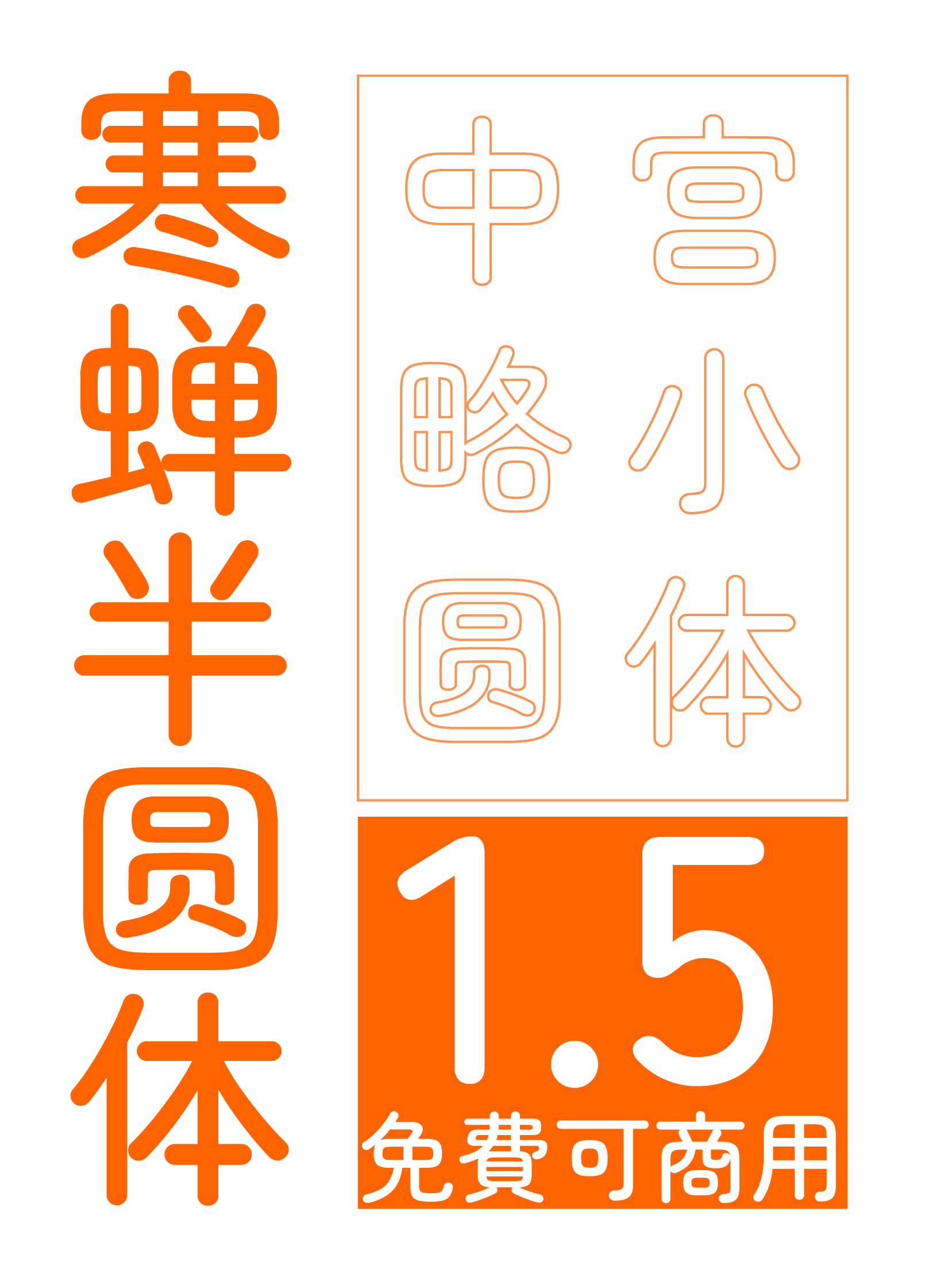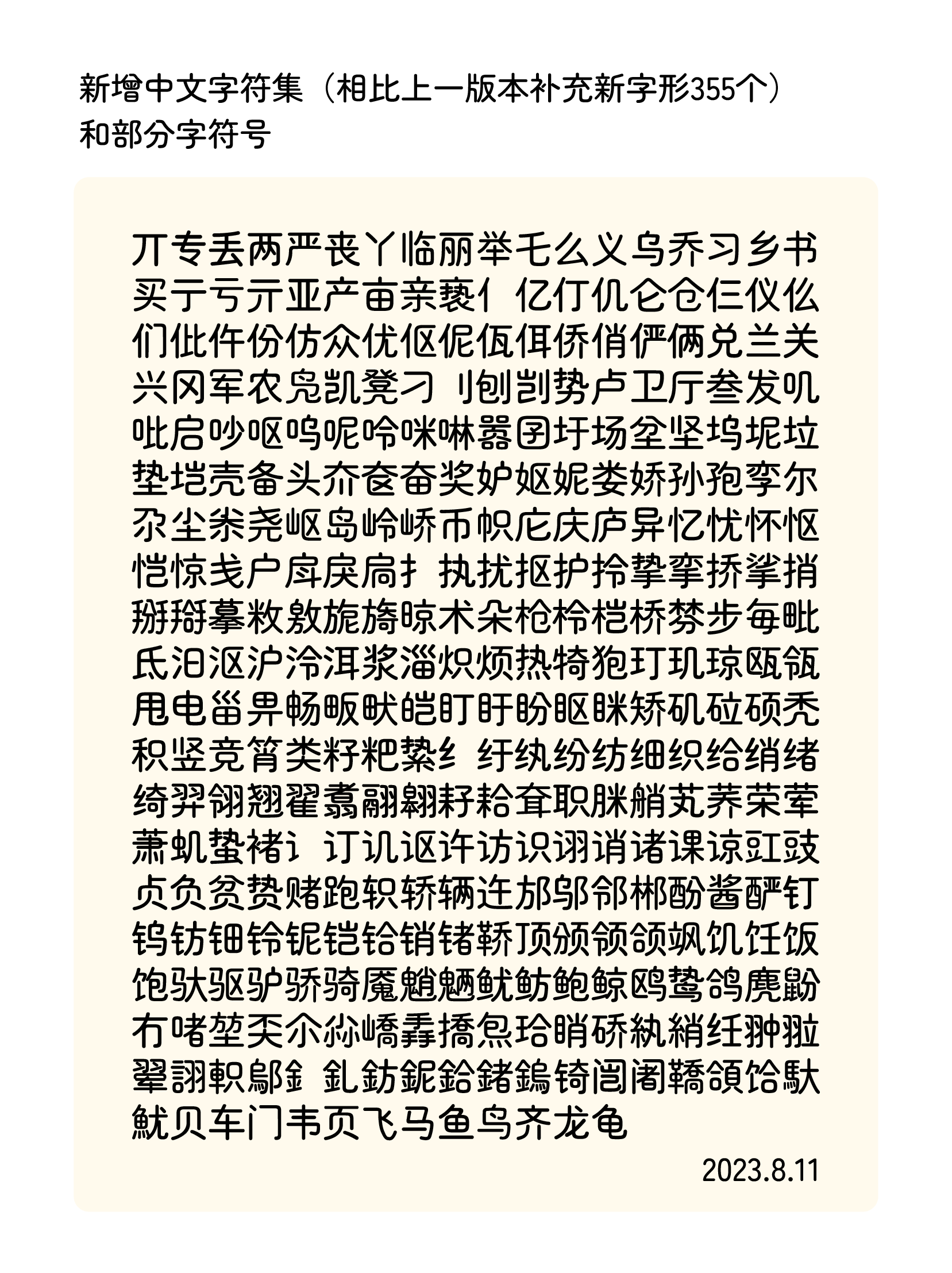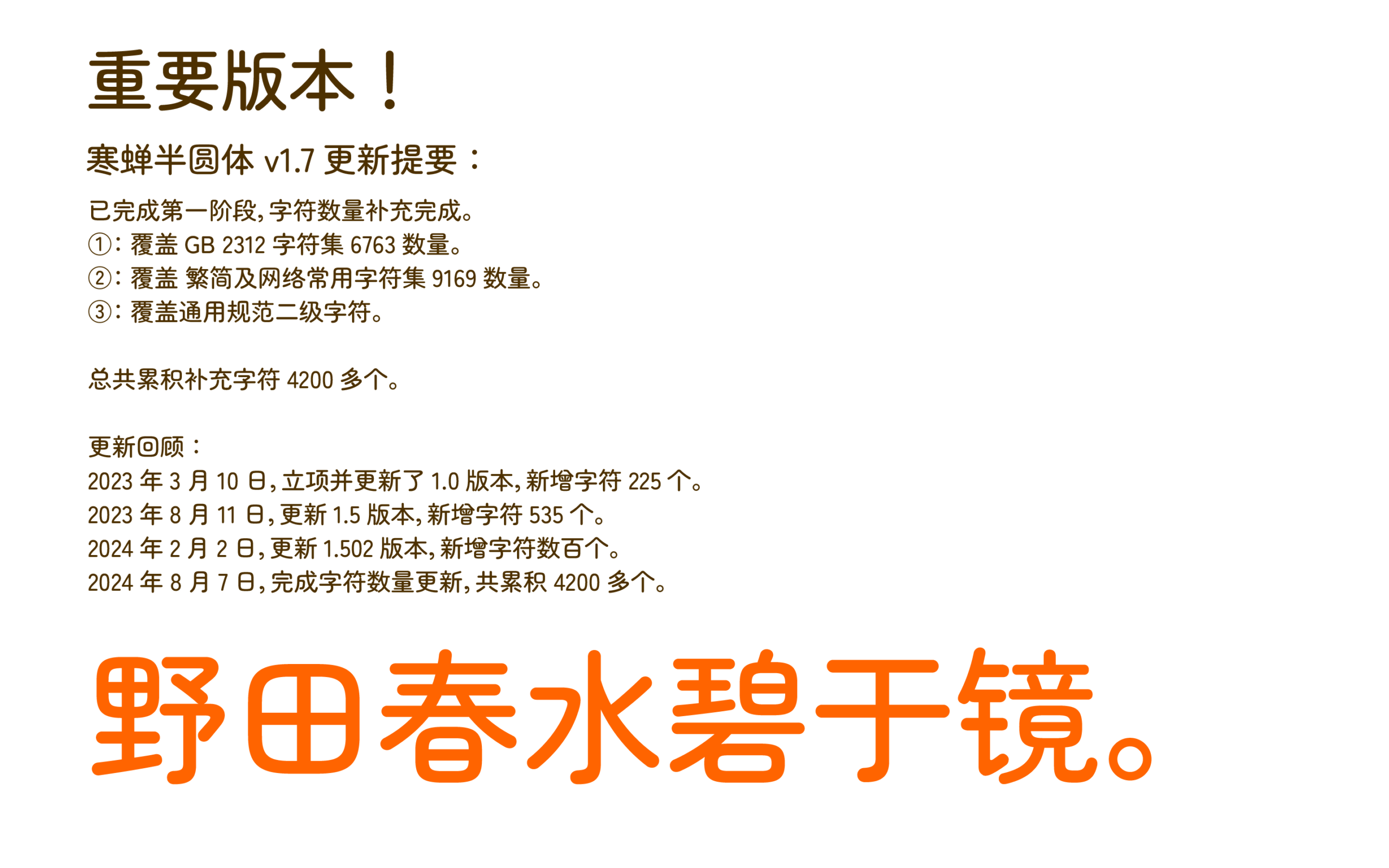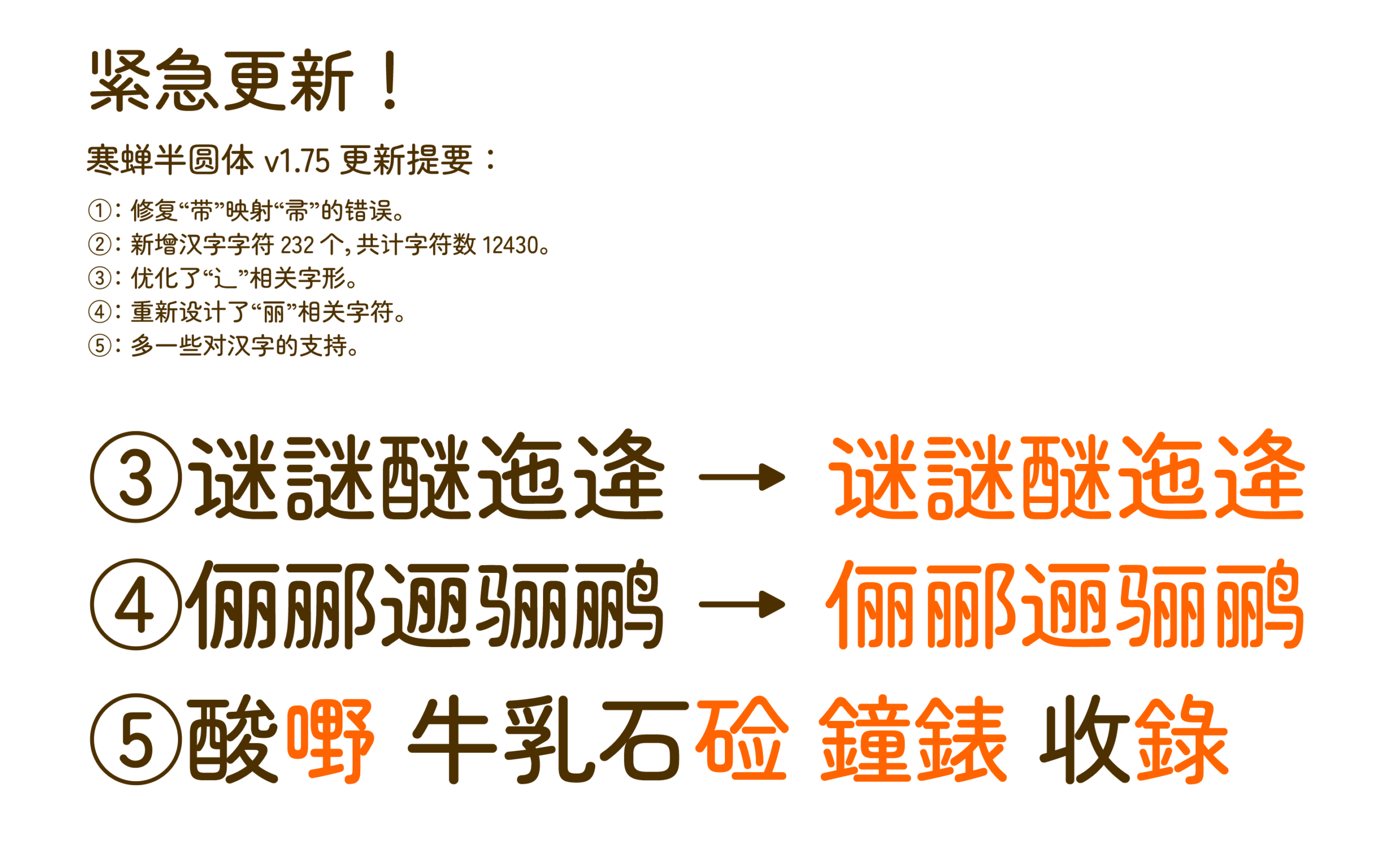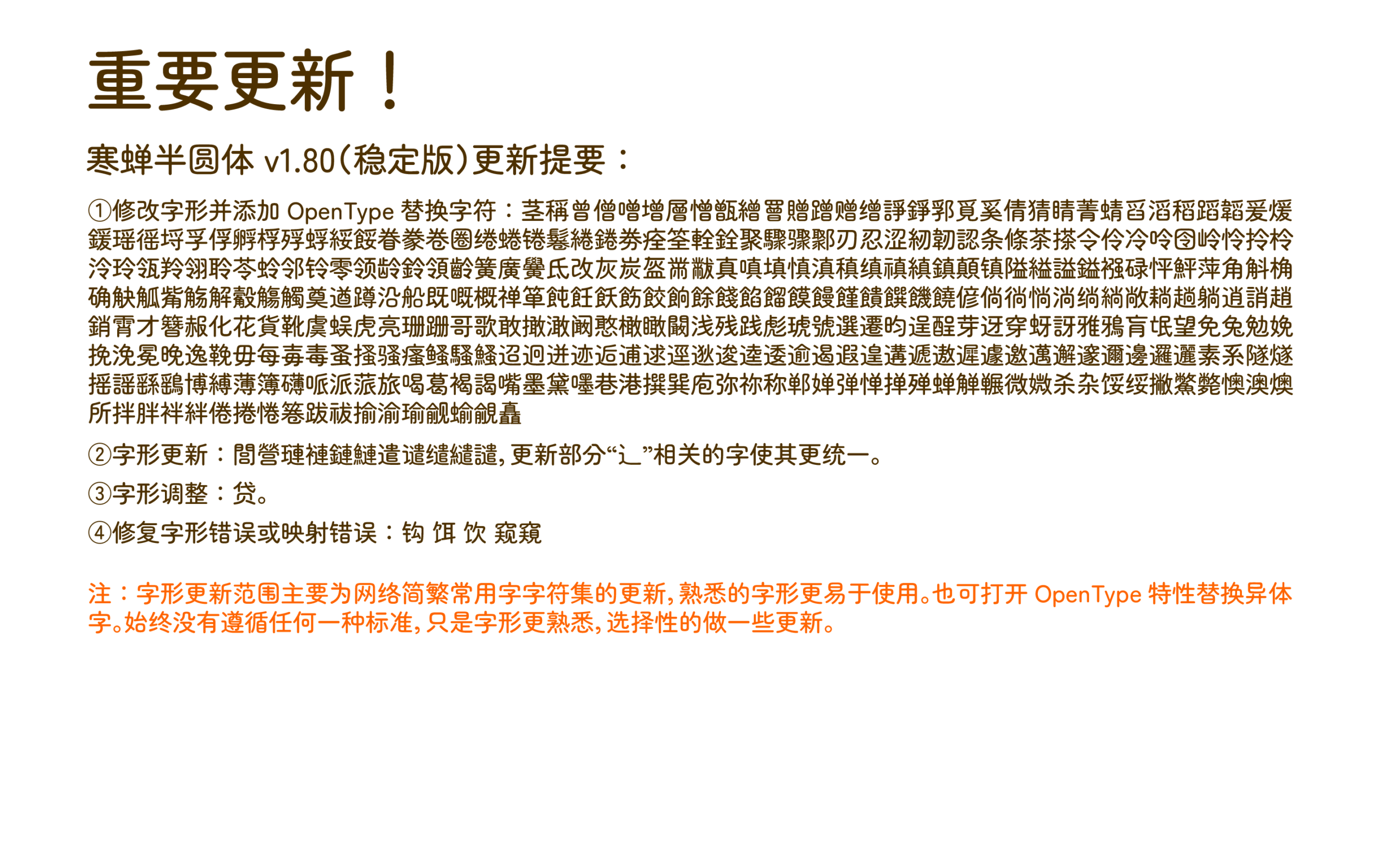
寒蝉半圆体 是一款基于日本开源字型 Zen Maru Gothic 进行深度优化与调整的中文圆体字型。该字型在继承原版柔和、亲切的圆润风格基础上,进行了全面的本地化改造,使其更完美地适配中文排版与使用需求。
其核心更新在于 字符集的全面升级:字型已更新为完全符合中华人民共和国国家标准 GB2312 的字符集。这意味着它涵盖了简体中文环境中几乎所有常用汉字、字母和符号,极大地扩展了其应用范围,无论是用于网页设计、印刷出版、UI界面还是日常办公文档,都能提供广泛而可靠的支持。
此外,对字型进行了精细的 字形修正与补充。这包括对部分原有字形在中文环境下的结构、笔画和重心进行修正,使其更符合中文书写习惯与审美。同时,还补充了 GB2312 标准范围内原先缺失或未包含的汉字,确保字型集的完整性与专业性。
在排版呈现上,寒蝉全圆体 经过仔细的调整与测试,致力于实现 更均衡、和谐的排版效果。无论是单字展示还是连续文本段落,其字距、行距以及笔画的视觉平衡都得到了优化,为用户提供更加舒适、流畅且美观的阅读与视觉体验。